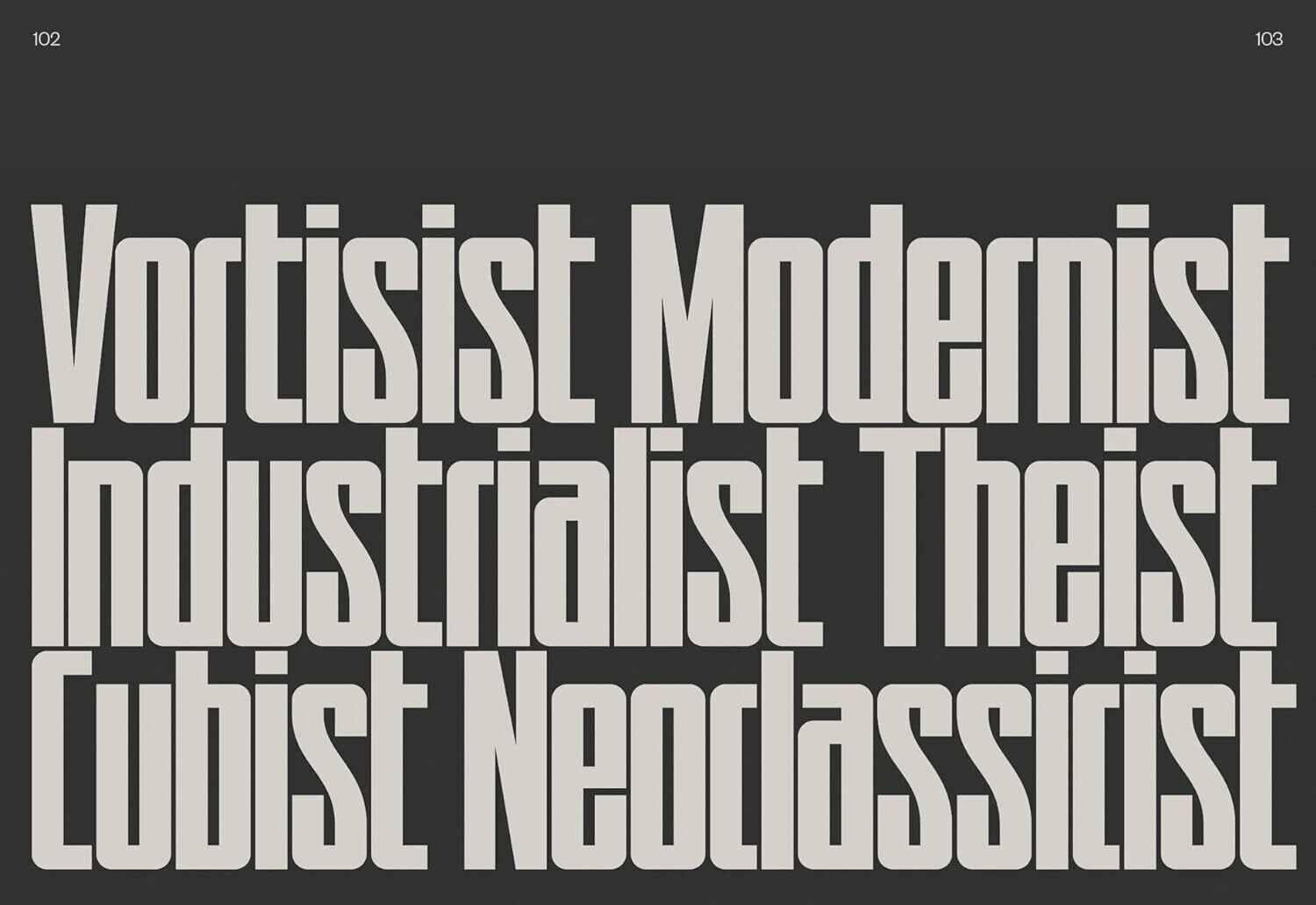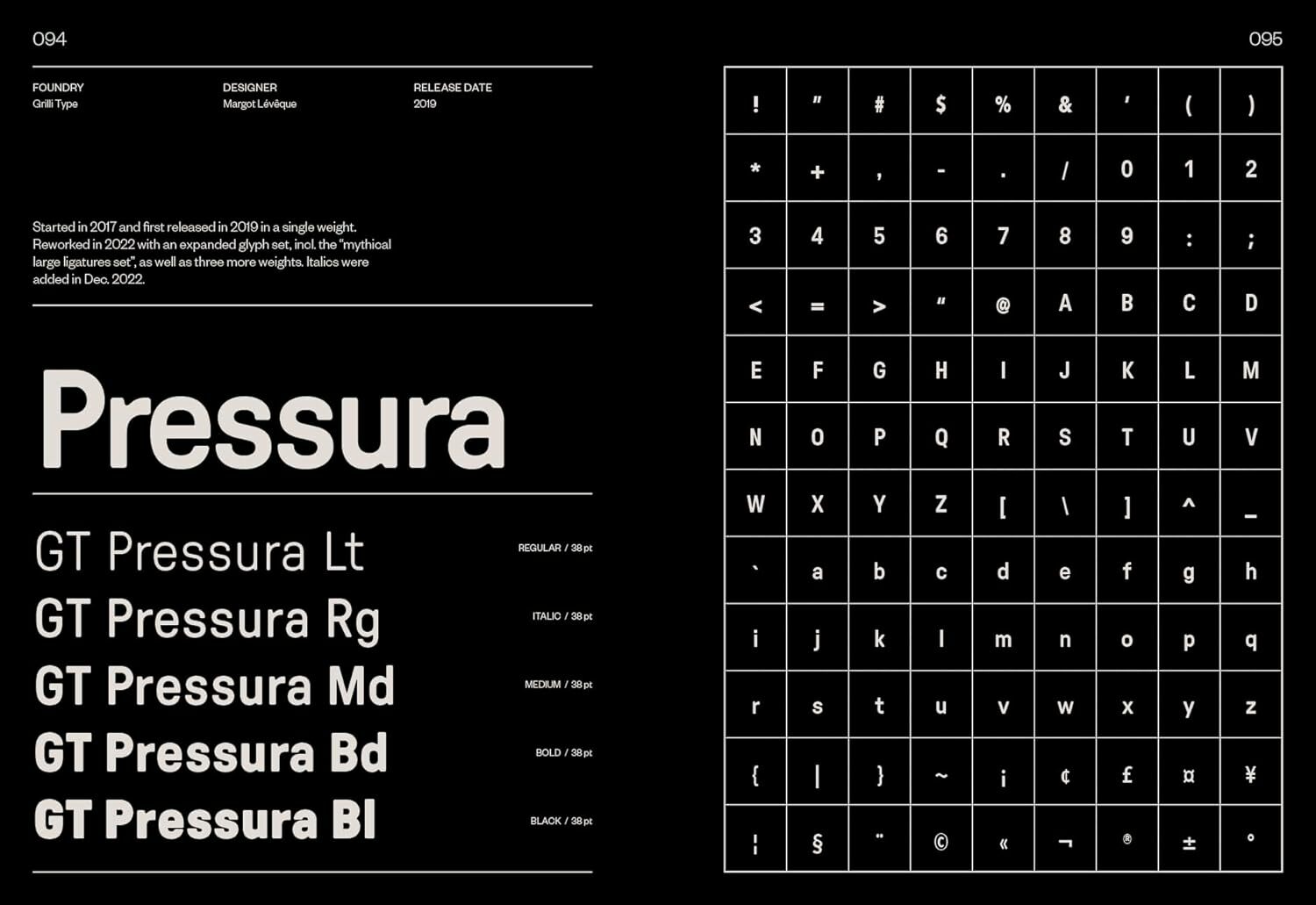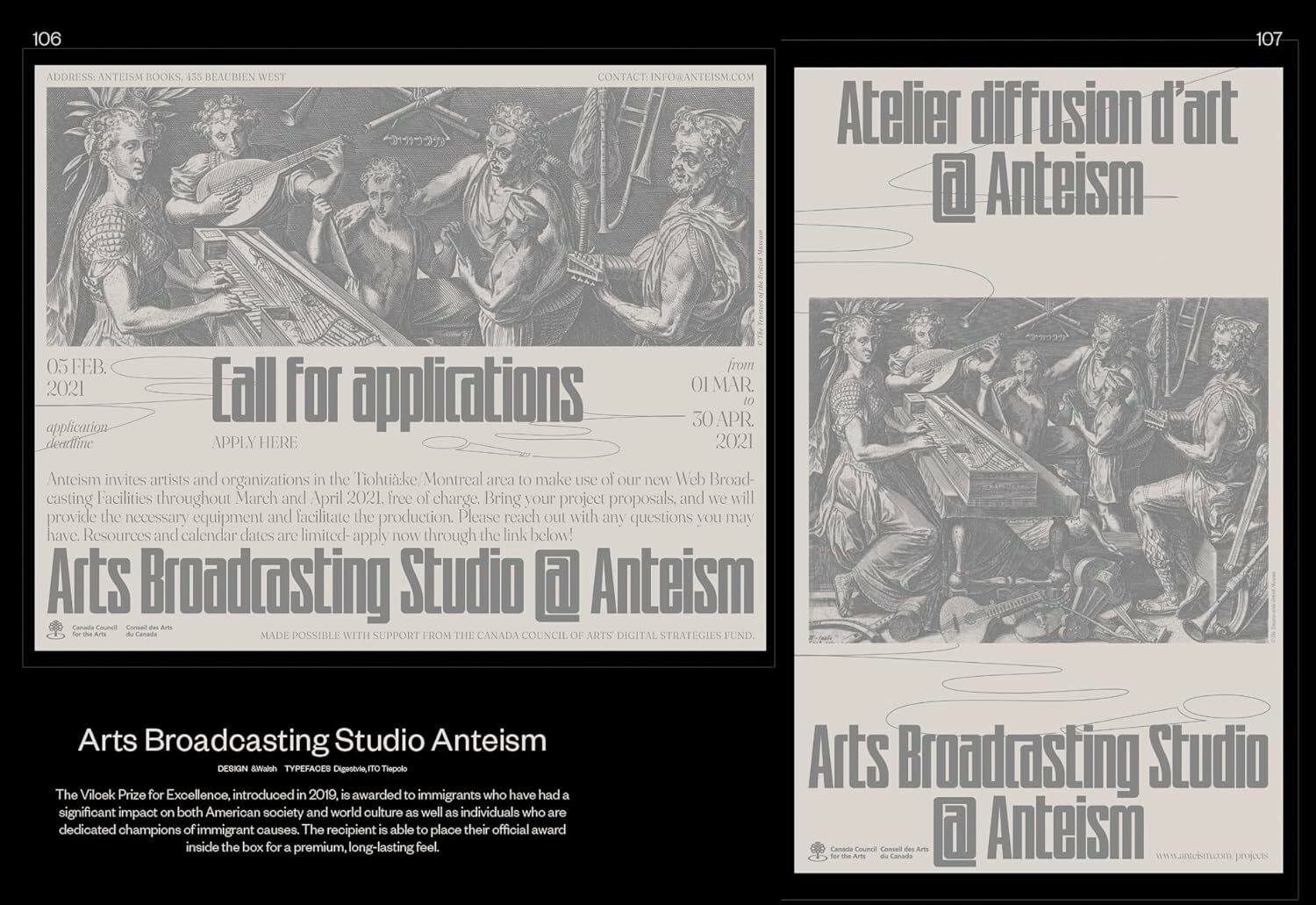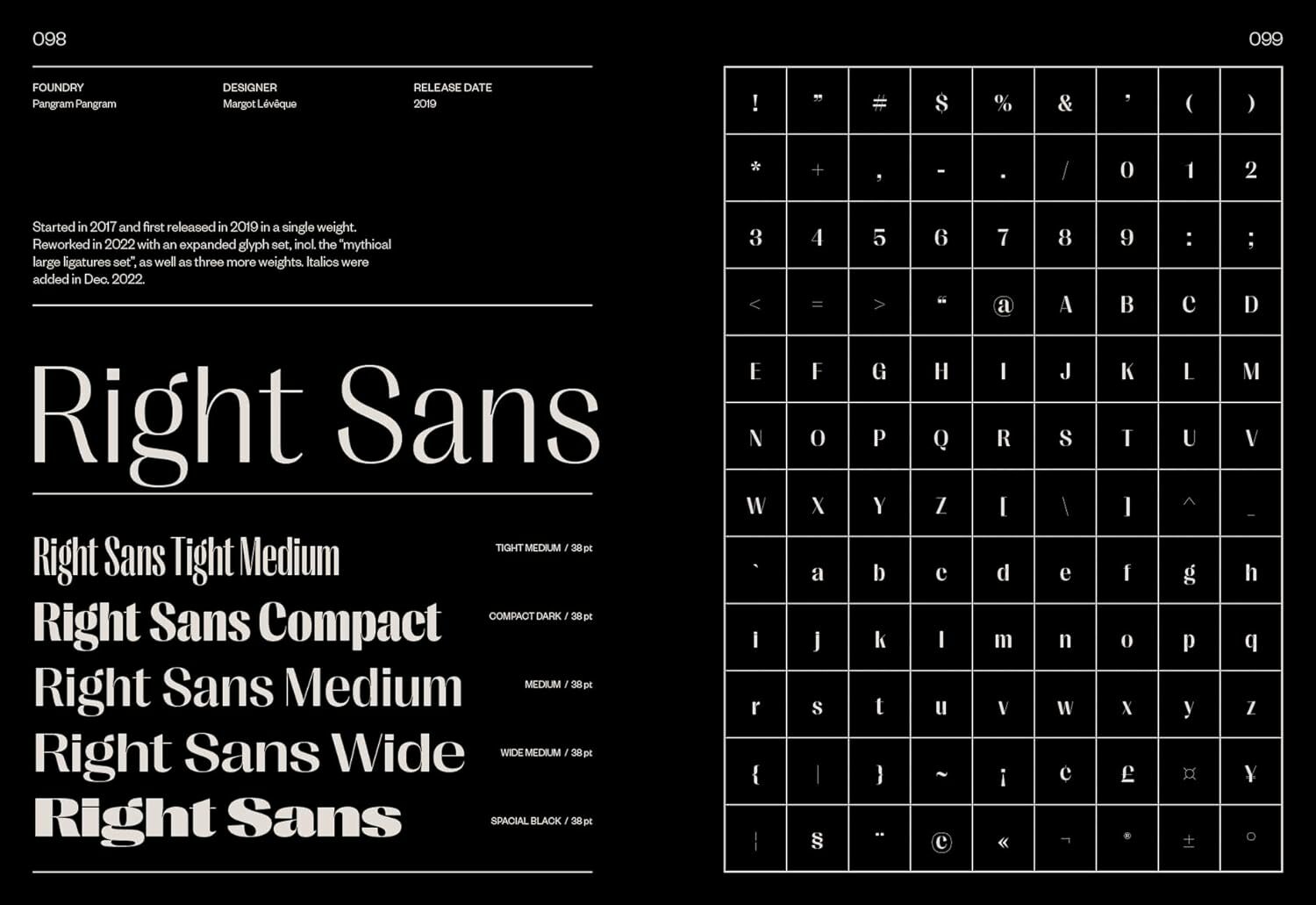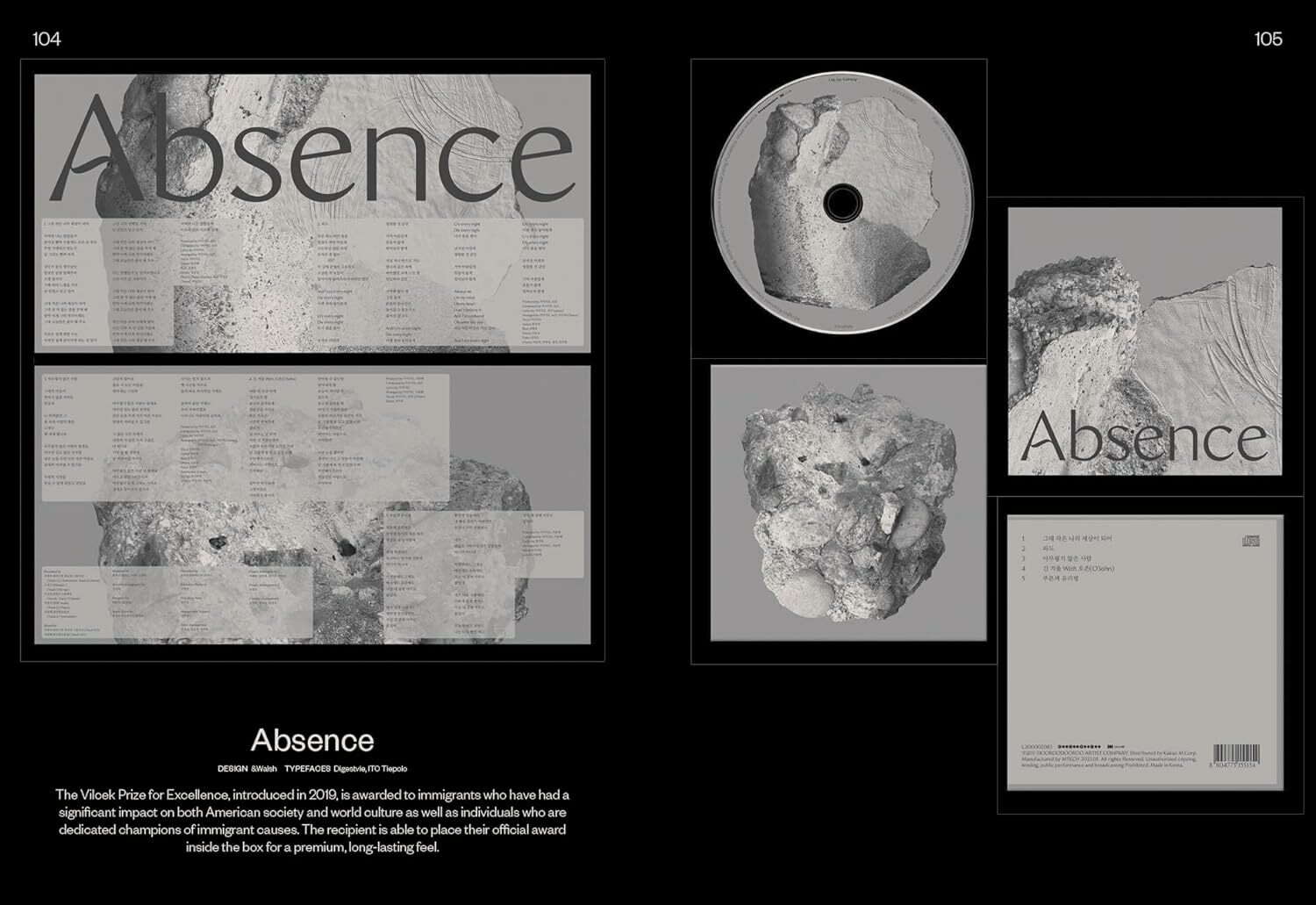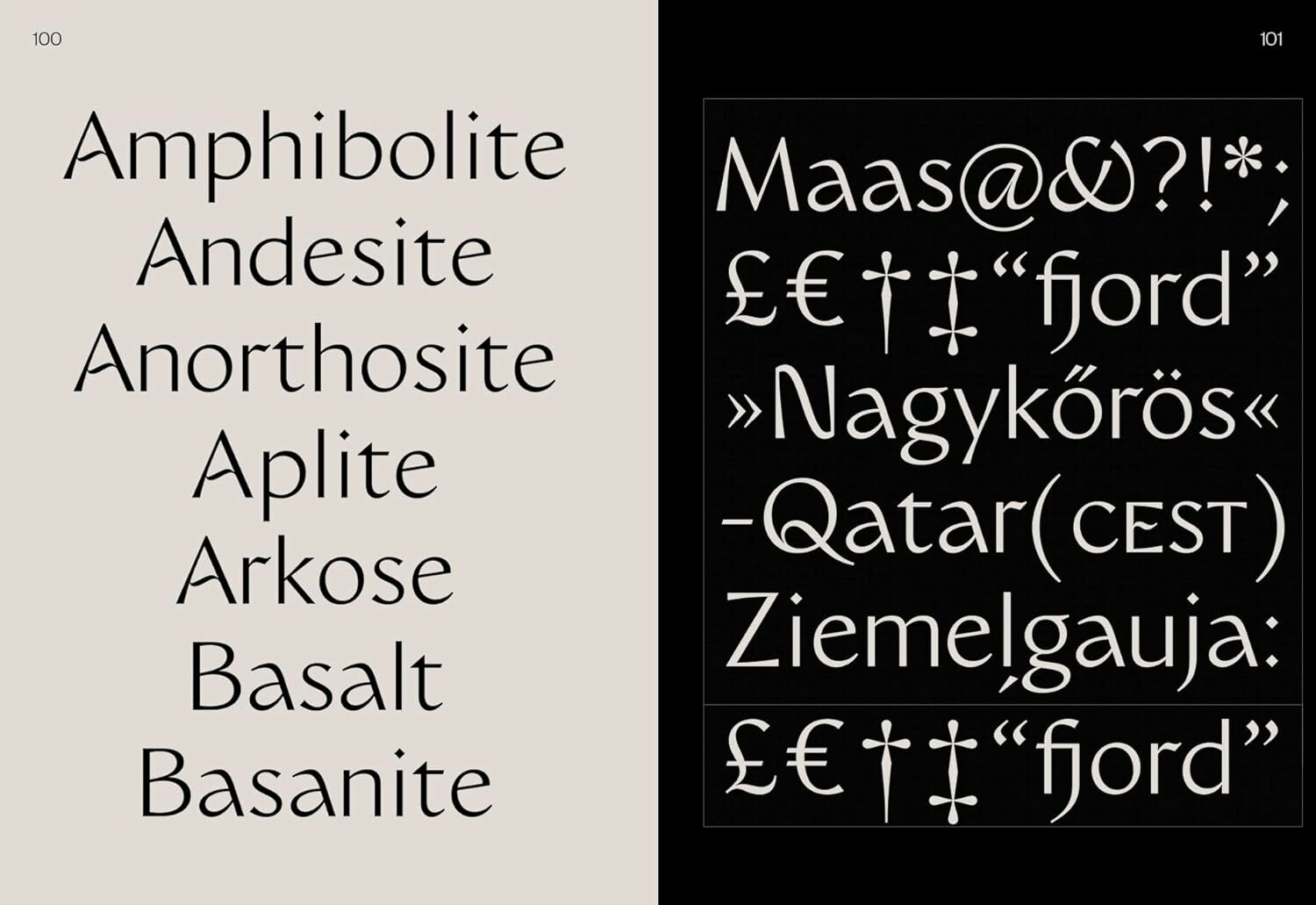
Sans In Use: A Collection of Sans Serif Typefaces
Sans Serif字體,也稱為無襯線字體,是指在字母的末端沒有裝飾性線條或筆畫的小延伸部分的字體。Sans Serif字體的特點和用途為字母末端沒有裝飾性的小筆畫,使得字體線條簡單明瞭。通常給人以現代、清晰和簡潔的感覺。Sans Serif字體在數位螢幕上更易於閱讀,因為它們在低解析度下不會失真。
由於其清晰性,Sans Serif字體廣泛應用於網站、應用程式和其他數位介面。其簡潔的設計使其易於快速識別,常用於品牌標識和公共標識。在印刷術的世界中,在同一設計中看到襯線和無襯線字體的組合並不罕見。然而,將它們結合起來需要技巧,以避免緊張和衝突,並確保設計中文本的最大可讀性。
從字體粗細到分類,每種字體都有其獨特的個性,應該仔細搭配以傳達設計的正確基調和情緒。 Sans in Use 精選了字體樣本、其設計應用以及工藝背後的思想,整理無襯線字體類的最佳組合,為尋求靈感的設計師和印刷師提供了參考。